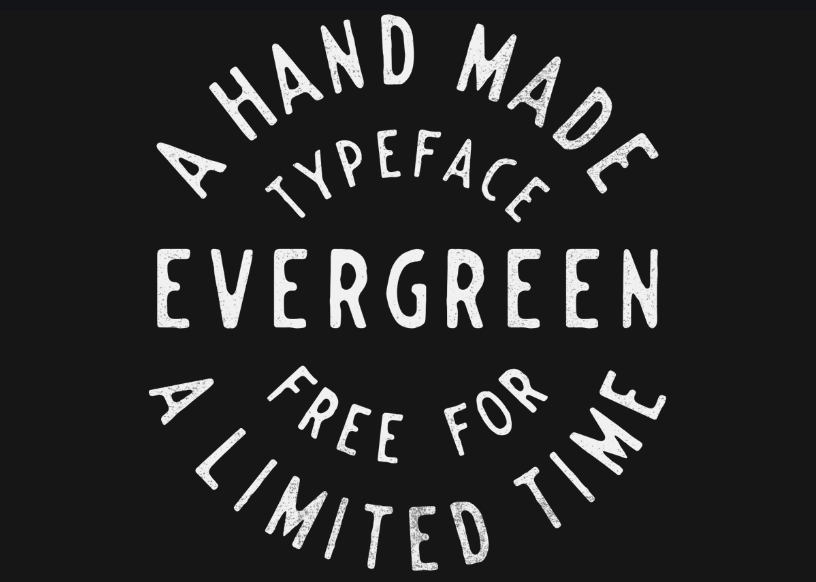
A EVERGREEN é uma fonte inspirada nas velhas placas com memória nostálgica, perfeita para quem ama a natureza e deseja adicionar um toque vintage aos seus trabalhos digitais. Inspirada por uma paixão pelo mundo exterior, esta font foi desenhada à mão antes de ser importada em formato digital, tornando-a única e personalizada. Eu maniqueamente preservei todas as bordas suaves e texturizadas do estilo da arte manual, garantindo um aspecto autêntico e único que irá destacar seus projetos. Esta font para escrita de teclado é perfeita tanto para uma mistura vintage quanto para criar designs mais modernos com suas linhas arredondadas e desenhos naturais. E como designer, Hamilton, entende a importância de trazer os detalhes originais e quase invisíveis da arte manual para o mundo digital, criando um recurso que combina tecnologia com beleza natural.